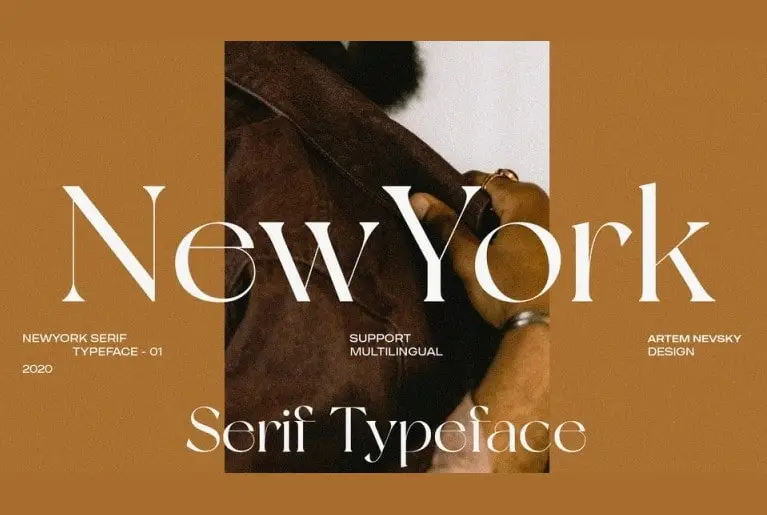
A New York Serif Font é uma tipografia serifada moderna e elegante que traz uma paixantela única aos seus projetos. Artyom Nevsky, o designer responsável pela criação desta fonte, soube capturar os elementos de simplicidade e sofisticação necessários para criar um design que atende a uma ampla gama de demandas profissionais. A New York Serif é perfeita para branding fashionista, gráficos em revistas, logos e arte social digital, apresentando sempre uma aparência respeitável sem comprometer o charme elegante do tipo serifado. Suas letras são tão variadas quanto bonitas, oferecendo uma experiência visual que vai do simples ao sofisticado, perfeitamente adaptada para qualquer projeto de design em que você esteja trabalhando. Sua versão para dispositivos móveis é um recurso adicional que torna a New York Serif Font ainda mais versátil e acessível para quem procura uma fonte moderna com toque clássico.